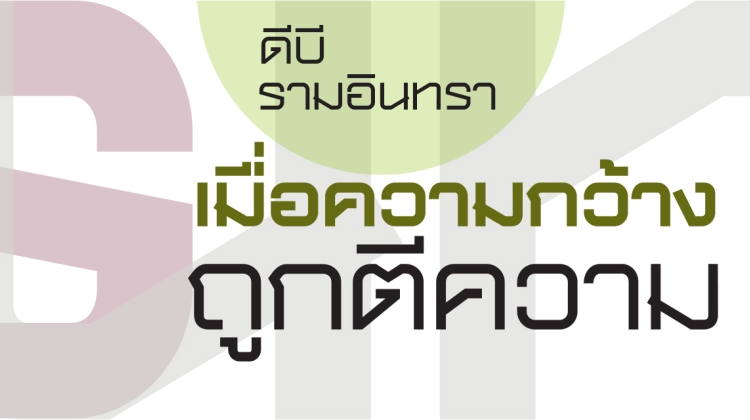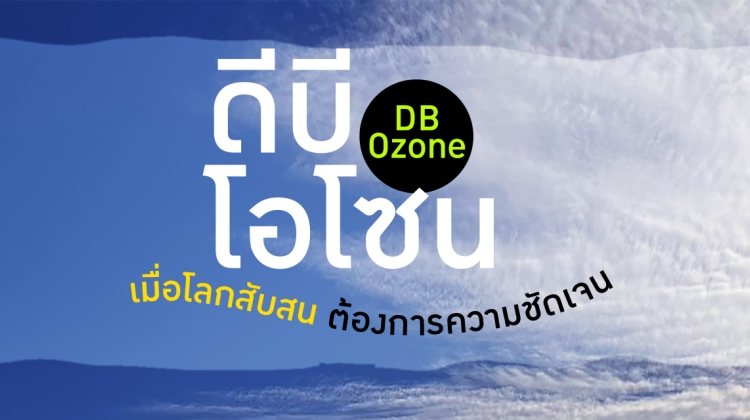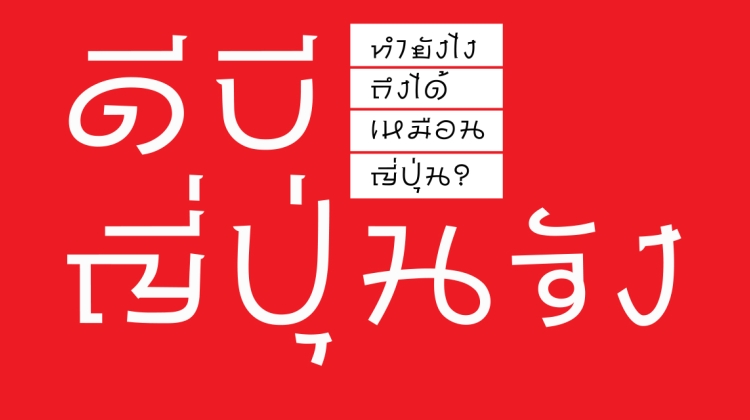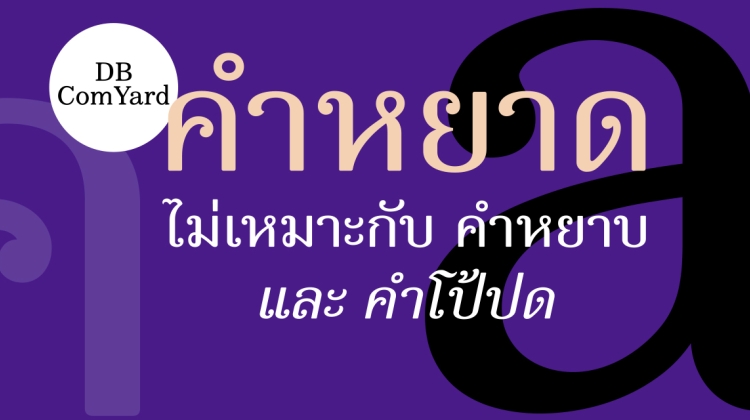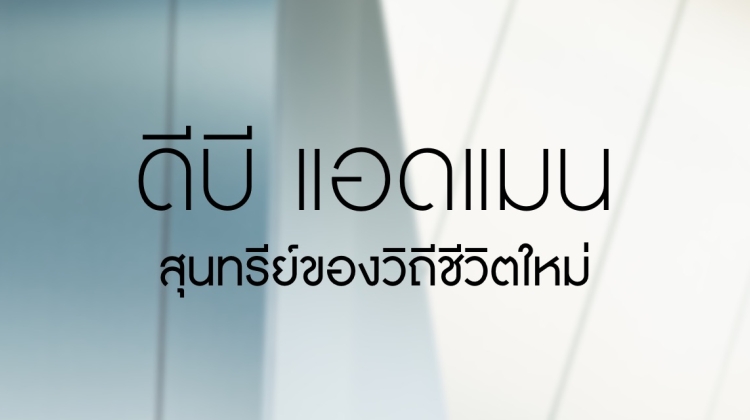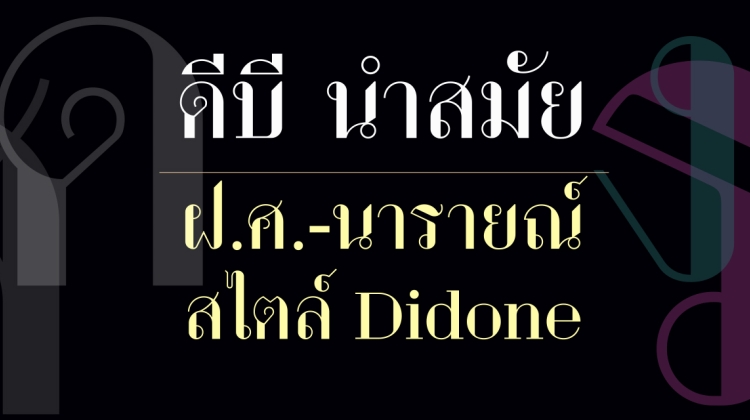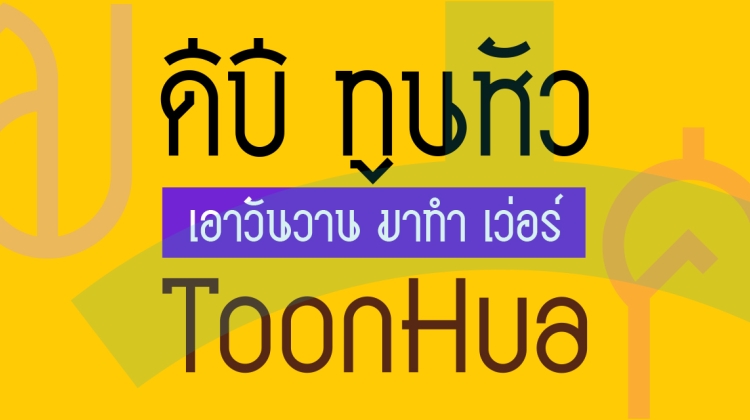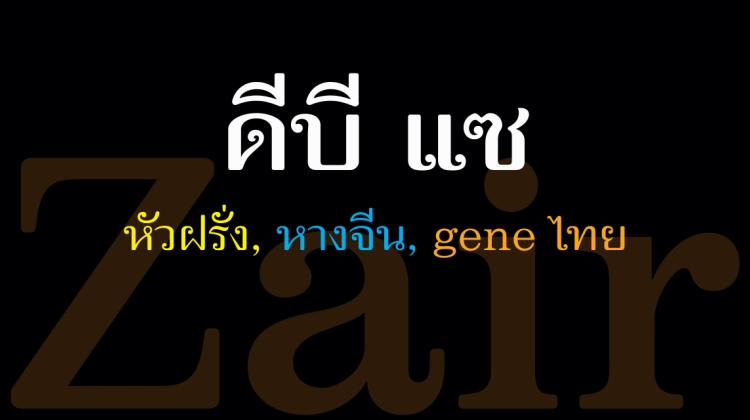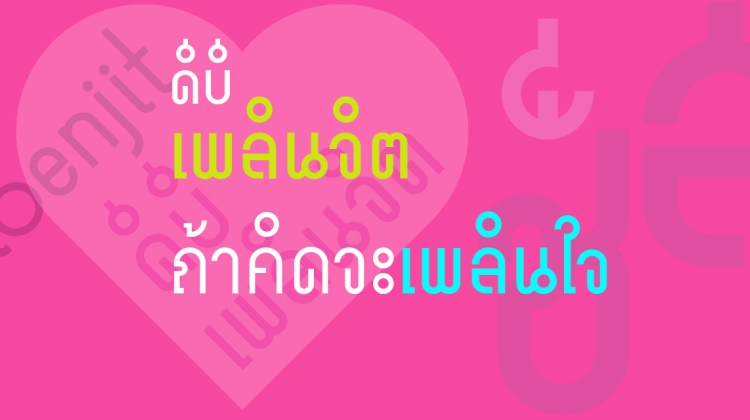
DB PuiMake
DB PuiMake คือสถานะใหม่ของ DB FongNam ที่ดูผ่อนคลายกว่า, ไม่ว่าจะใช้ขนาดเล็กๆ เป็นตัวเนื้อ หรือใช้พาดหัวใหญ่ก็ตาม.
DB ChuanPim
‘ชวนพิมพ์’ คือแบบตัวเรียงพิมพ์ด้วยแสงของไทย ที่ได้รับการยอมรับว่าเป็นตัวเนื้อที่ดูสะอาดเรียบง่ายเทียบได้กับ Helvetica. ปัจจุบันได้รับการอนุรักษ์ไว้เป็น OpenType ชื่อ DB ChuanPim X โดยเพิ่มน้ำหนักเข้าไปจากเดิมซึ่งมีเพียงน้ำหนักเดียวเป็น 4 น้ำหนัก.
DB PloenJit
เป็นผลงานอนุรักษ์แบบตัวอักษรประดิษฐ์รูปทรงเรขาคณิตยุคต้นๆ ของไทยที่มีแบบฉบับของไทยเอง
DB Zair
เป็นงานอนุรักษ์แบบตัวพิมพ์ตะกั่วพาดหัวหนังสือพิมพ์ และโฆษณาในเมืองสยาม ที่ชื่อ ‘โป้งแซ’ ผลงานออกแบบและแกะแบบโดย นายแซ ช่างแกะแบบตัวพิมพ์เชื้อสายจีนที่มีฝีมือสูงในยุคนั้น.
DB ToonHua
DB ToonHua เป็นฟอนต์พาดหัวไทยแท้ ที่พัฒนามาจากกรุตัวอักษรเก่าๆ ทั้งที่เป็นแบบตัวเรียงพิมพ์ตะกั่ว ไปจนถึงตัวประดิษฐ์หลอมรวมกันใหม่ โดยอาศัยรูปทรงเรขาคณิตง่ายๆ
DB NamSmai
รากเหง้าจริงๆ ของ DB NamSmai มาจากแบบตัวเรียง พิมพ์ตะกั่วที่มีความสําคัญมากชุดหนึ่งของไทย ในฐานะตัวพิมพ์เนื้อชุดแรกที่มีเส้นหนักเบาอย่างตัวพิมพ์โรมัน, ตัวพิมพ์ที่ว่านี้คือ ‘ฝรั่งเศส’ หรือที่นิยมเรียกตามชื่อย่อว่า ‘ฝ.ศ.’
DB Adman
เมื่อโลกตะวันตกก้าวสู่ยุคอุตสาหกรรม มีตัวพิมพ์แหวกแนวชุดหนึ่งถือกําเนิดขึ้นโดยฝีมือ Paul Renner ผู้เป็นทั้งนักออกแบบหนังสือและนักเขียน, หน้าตาของตัวพิมพ์ชุดนั้น ดูราวกับเกิดขึ้นจากเครื่องมือเครื่องจักรแห่งอารยธรรม
DB ComYard
ตัวอักษรประดิษฐ์ของไทยแบบหนึ่ง ซึ่งแม้จะไม่มีหัวกลม แต่ก็ยังสามารถคงลักษณะจารีตประเพณีไว้ได้เป็นอย่างดี, คือ แบบตัวอักษรซึ่งมีหัวเปิด ขมวดปมกลมๆ ที่ส่วนปลายคล้ายยอดอ่อนของใบเฟิร์น, ลักษณะที่ว่านี้สามารถพบเห็นในแบบตัวพิมพ์ Clarendon ที่ออกแบบโดย Robert Besley ตั้งแต่ปี ค.ศ.1845
DB YeePunJung
ต้องยอมรับว่า นอกจากวัฒนธรรมจีน, ตะวันตกที่มีอิทธิพลต่อคนไทยมาช้านานแล้ว วัฒนธรรมญี่ปุ่นก็ซึมเข้ามาไม่น้อย ทั้งอาหารการกิน, การ์ตูน, แฟชั่น ฯลฯ แต่กลับไม่มีฟอนต์ความยืดหยุ่นสูงคล้ายลักษณะนิสัยของคนไทย
DB Ozone
DB Ozone เป็นฟอนต์ดิสเพลย์ไทย สไตล์โรมันที่ได้รับ DNA มาจากฟอนต์ DIN (Deutsche Industrial Norm), ลักษณะสําคัญ ของ DIN ที่ตกทอดมาถึง DB 0zone ที่เห็นได้อย่างเด่นชัด 2 ประการ คือ การเดินเส้นแบบเรขาคณิต และช่องไฟที่โปร่ง
DB Ramintra
ความกว้างของรูปอักษร (glyph) ให้ความรู้สึกโอ่อ่า ฐานที่กว้างให้ความรู้สึกมั่นคง. รูปทรงจัตุรัสที่เกิดจากเส้นน้ำหนักเดียว (Monoline) ให้ความรู้สึกทันสมัยเรียบง่าย. เมื่อถูกลบมุมช่วยลดความแข็งลง. ถ้าเส้นบางจะเหมือนห้องปลอดโปร่ง ถ้าเส้นหนาจะดูหนักแน่นแข็งแรง. นี่คือความเป็น Eurostile Extended.
DB Sathorn
คือความพยายามของผมที่จะสร้างฟอนต์ตัวพาดหัวไทย ที่สามารถทดแทนตัวอักษรลอกตระกูล Manoptica (มานพติก้า) ซึ่งครองเมืองในยุคที่คอมพิวเตอร์ยังไม่เป็นที่ใช้แพร่หลาย